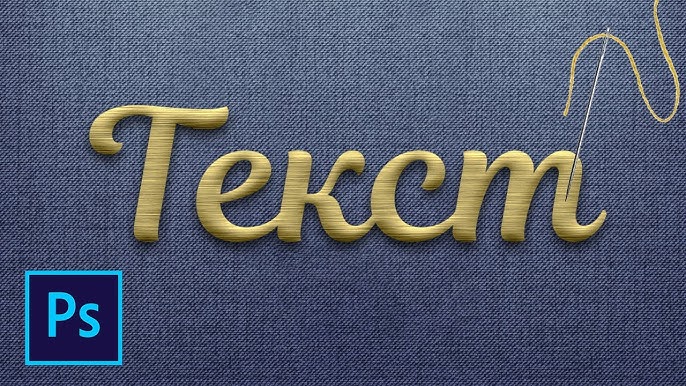
Идеи по разноцветному тексту: как сделать его ярким и привлекательным для глаз
Хотите узнать, как придать своему тексту новые оттенки и краски? В данной статье вы найдете полезные советы и техники для создания разноцветного шрифта, который сделает ваш текст неповторимым и привлекательным.
Как сделать разноцветный текст в фотошопе
Используйте градиент: сочетание разных цветов в тексте придаст ему объем и глубину.
Экспериментируйте с контрастными комбинациями: сочетание ярких цветов с темным или светлым фоном будет выглядеть эффектно.
Не забывайте о читаемости: выбирайте цвета, которые хорошо видны на заднем фоне и не вызывают напряжения глаз.